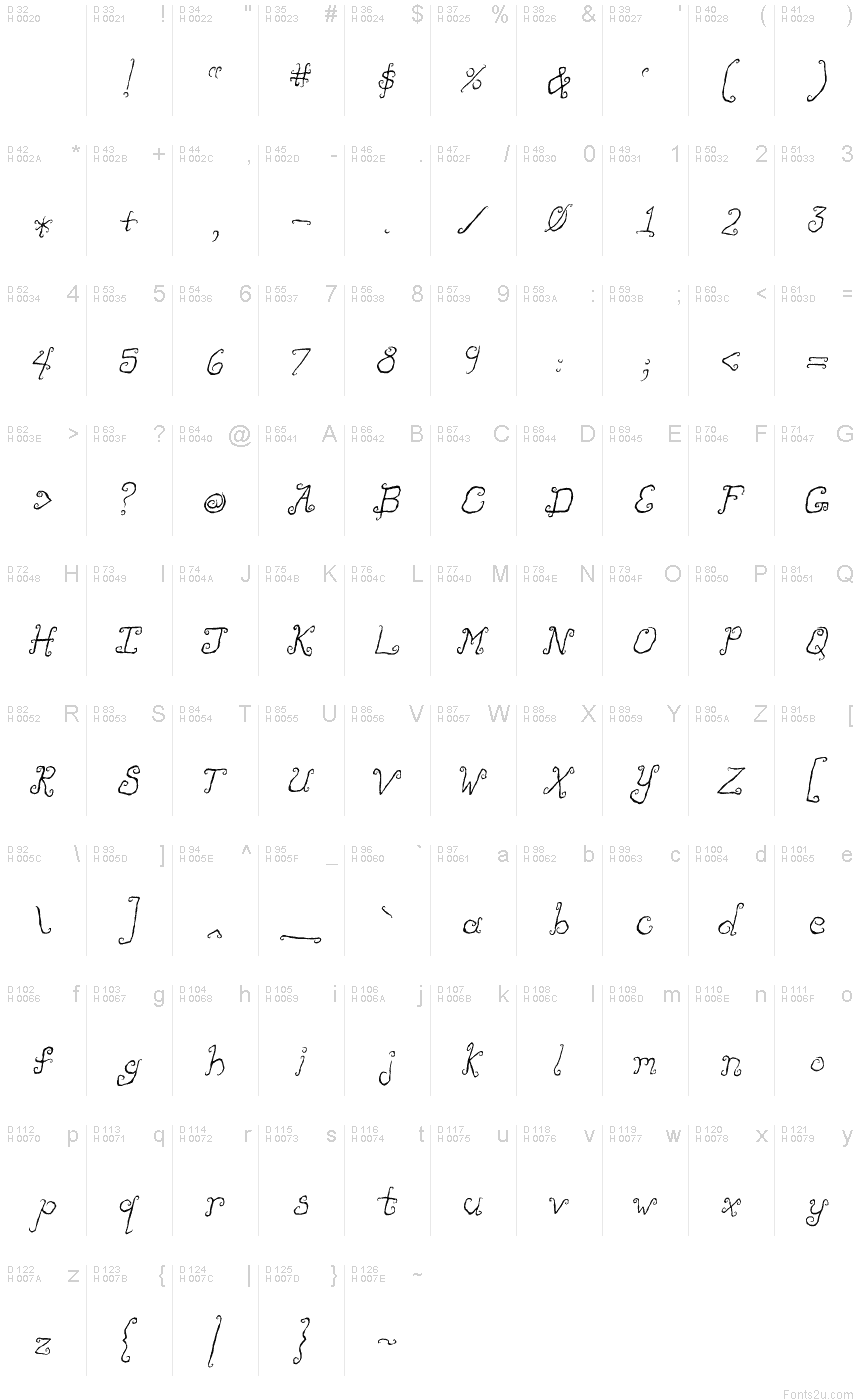
Like Cockatoos Italic
Like Cockatoos Italic autorstwa Kevina Richeya to darmowy, ozdobny krój pisma o swobodnym, odręcznym charakterze, który przywodzi na myśl świat baśni. Litery wyróżniają się długimi, pętlowymi pociągnięciami i zawiniętymi końcówkami, dzięki czemu cały projekt wydaje się lekki, zabawny i nieco ekscentryczny, a nie surowy czy formalny.
Świetnie sprawdzi się w tytułach na plakatach, kartkach okolicznościowych, rękodziele, okładkach książek, kawiarnianych szyldach kredowych czy krótkich wyróżnieniach tekstowych, gdzie te kręte linie mogą grać pierwsze skrzypce. Jako darmowy font, nadaje się również do plansz tytułowych, szkiców logo i inicjałów w formie monogramów – idealny, gdy szukasz fantazyjnego kroju, który nie przytłacza słodyczą.